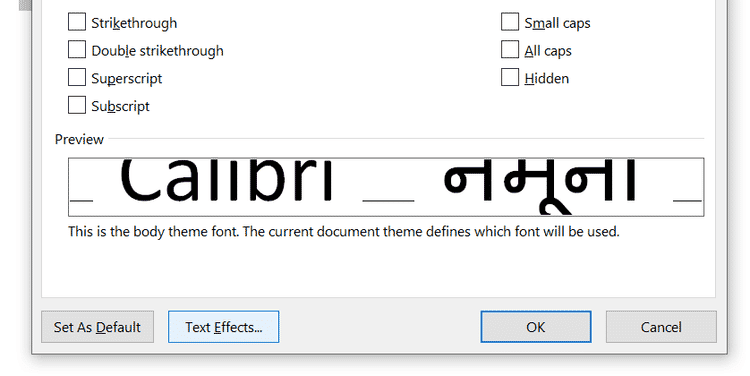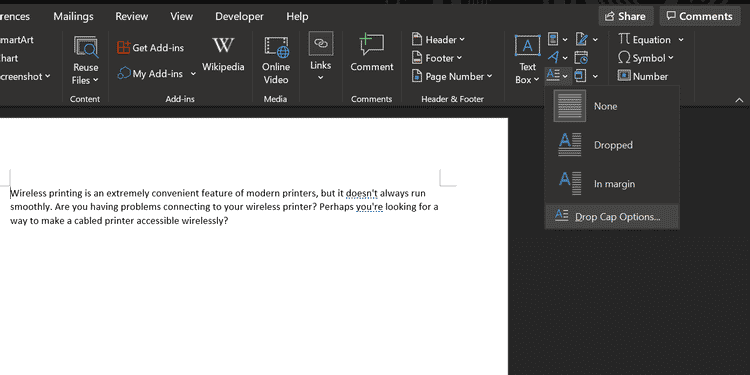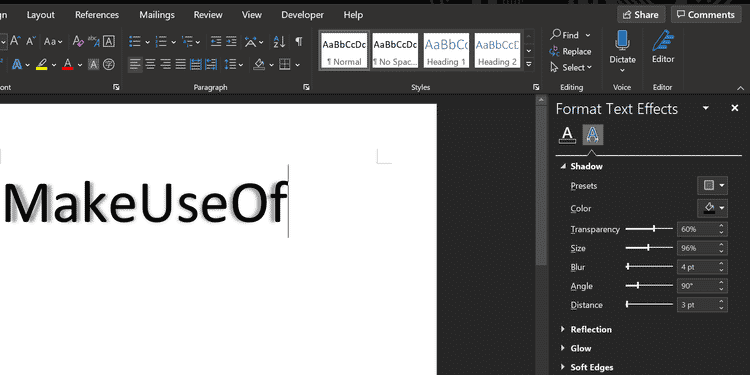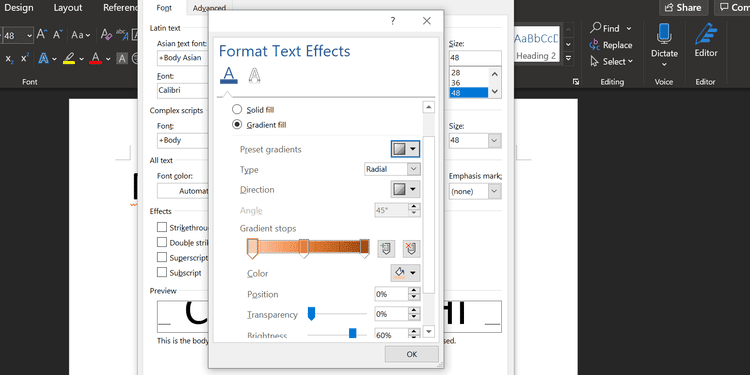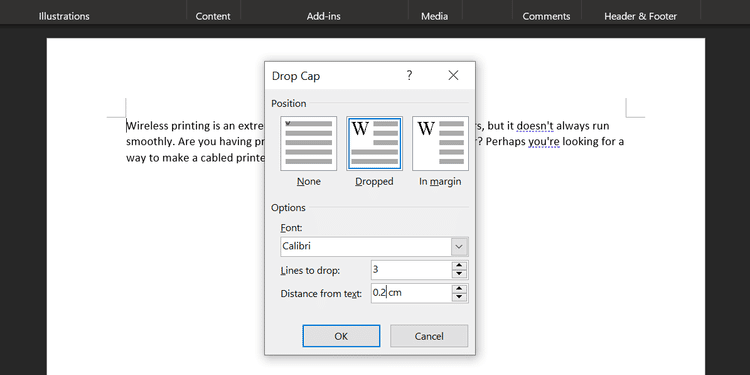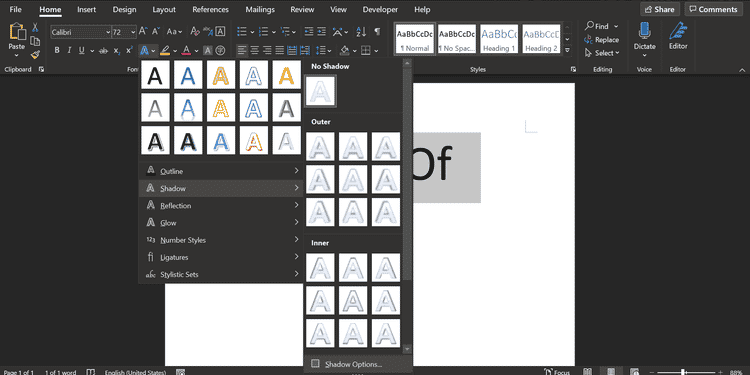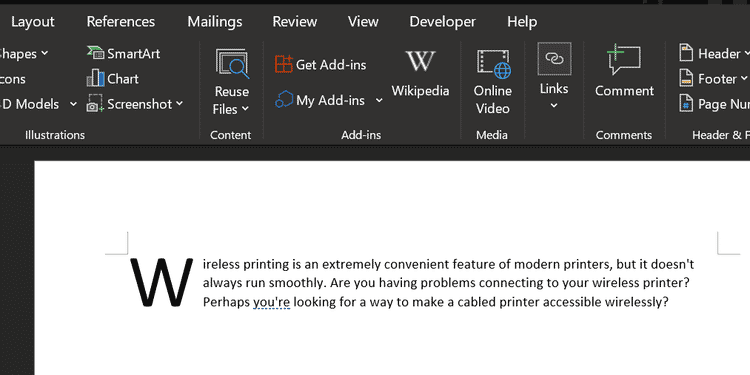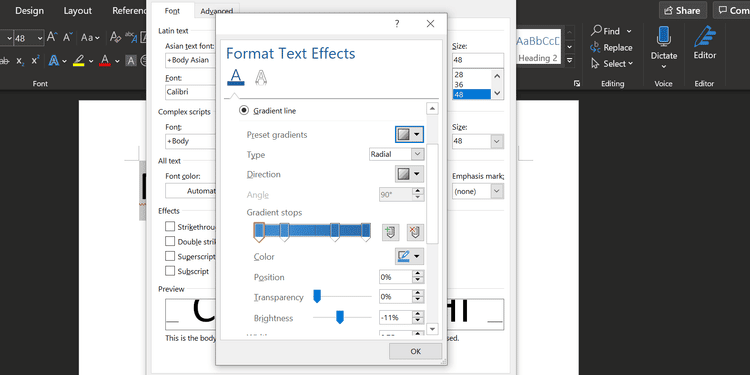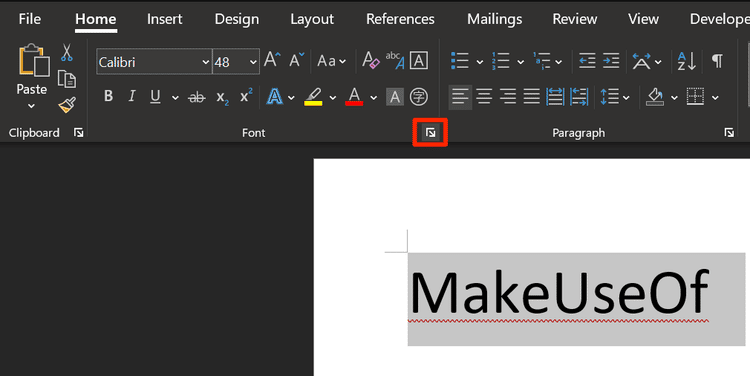
لمجرد رؤية صفحات من النص العادي يُمكن أن يجعل جفونك تبدأ في التدلي. تُشير مستندات Word غير المُنسقة إلى أن هذه القراءة ستكون مُحبطة ومُملة. لا أحد يُريد أن يتحمل هذا النوع من الملل.
يحتوي Microsoft Word على العديد من الأدوات التي يُمكن أن تجعل النص الخاص بك أكثر جمالا مع الخطوط الجمالية والتأثيرات الدقيقة. يُمكن للمبالغة في ذلك أن تملأ المستند بإلهاءات ، لكن الأسلوب المعقول في التصميم والديكور يُضيف اهتمامًا بصريًا مُهمًا للحفاظ على انتباه القارئ.
إليك بعض أنماط الخطوط وتأثيراتها لإبراز النص في Microsoft Word.
1. تثبيت الخطوط الجمالية لـ Microsoft Word
تتمثل إحدى أسهل الطرق لإضفاء الحيوية على النص في Word في إضافة بعض الخطوط الجديدة. يُمكنك العثور على الكثير من الخطوط المجانية عبر الإنترنت ، ولكن الأمر يستحق أخذ لحظة للنظر فيما إذا كنت تريد استخدام تنسيق OTF أو TTF قبل أن تبدأ البحث.
هذه إصدارات معدلة قليلاً من الخط بأبعاد معدلة — يمكن أن تكون مفيدة جدًا إذا كنت تبحث عن الكمال ، ولكن سيتم تقديم خدمة جيدة لمعظم المُستخدمين من خلال الإصدار العادي وحده.
ثم ببساطة حدد الخط الجمالي الجديد من خيارات التنسيق داخل Microsoft Word.
2. إضافة ظل بسيط
الظل المُسقط هو أسلوب تصميم رسومي كلاسيكي يُمكنك استخدامه لإبراز النص. يُقدم Word عدة طرق مختلفة لتحقيق ذلك ، ويُمكنك استخدام قائمة تأثيرات النص والكتابة للقيام بذلك.
أولاً ، اكتب النص الذي تُريده ونسق حجمه وخطه وفقًا للمُواصفات التي تُفضلها — ستحتاج إلى تحديد الشكل الذي تُريده أن يبدو عليه قبل إنشاء الظل الخاص بك. حدد النص الخاص بك باستخدام الماوس ، وانقر فوق أيقونة تأثيرات النص وصياغة الحروف (الزر A الأزرق) ، ثم حدد ظل متبوعًا بـ خيارات الظل.
سيتم فتح قائمة جديدة على اليمين تُتيح لك تخصيص الظل. إما أن تنقر فوق خيار الإعدادات المسبقة واختر أحد خيارات الظل العديدة أو اضبط الإعدادات المُختلفة بنفسك لإنشاء ظل مخصص.
سترى المعاينة المباشرة على يسار قائمة الظل.
استمر في تغيير الخيارات حتى يظهر الظل بالطريقة التي تُريدها. يُمكنك بعد ذلك النقر فوق الرمز X في الزاوية العلوية اليمنى من قائمة الظل لإغلاقها. يحفظ Word التغييرات التي تم إجراؤها على النص تلقائيًا.
3. إضافة حرف استهلالي مسقط
الحرف الاستهلالي المسقط هو الحرف الأول الكبير من الفقرة ، وغالبًا ما يوجد في الروايات القديمة. يُمكن لـ Microsoft Word تجهيز المستند الخاص بك بهذا العنصر الزخرفي الذي يجذب الانتباه في غضون ثوانٍ ، مما يمنحك وسائل إضافة الاهتمام إلى كتلة كبيرة من النص ، أو ببساطة استدعاء إلى الذهن حقبة كلاسيكية.
توجه إلى قسم النص في علامة التبويب إدراج وابحث عن القائمة المنسدلة إسقاط. ستتمكن من إنشاء حرف استهالي بسيط للغاية عن طريق تحديد إما تم إسقاطه أو في الهامش هنا ، ولكن للحصول على أفضل النتائج ، ستحتاج إلى النقر فوق خيارات اسقاط الأحرف الاستهلاكية ، بينما تم تحديد الحرف الأول من الفقرة.
حدد تم إسقاطه واضبط المسافة من النص إلى 0.2 سم (0.08 بوصة). قد تحتاج إلى تعديل المقدار ، اعتمادًا على الخط الذي تستخدمه والمقياس الذي تعمل به ، ولكن يُمكن أن يبدو الحرف الاستهلالي أحيانًا غير جيد مقارنةً بمسافة الأسطر القياسية عند تركه عند 0.
سيكون اختيارك للخط هو المفتاح للتأثير الكلي. يمكن أن يعمل sans font بشكل جيد إذا كان هدفك الأساسي هو مظهر لافت للنظر ، ولكن يمكن تحقيق غطاء مسقط تقليدي أكثر باستخدام خط serif الأكثر وضوحًا.
4. استخدام تأثيرات النص
إذا تم استخدامها بلا مبالاة ، يُمكن لتأثيرات النص المُتوفرة في Microsoft Word أن تُذكر بسهولة بأسوأ تجاوزات WordArt. ومع ذلك ، طالما أنك لا تفرط في استخدامها ، يمكن أن تمنح هذه التأثيرات المستند الخاص بك بعض التأثير البصري الحقيقي.
للوصول إلى قائمة تأثيرات النص ، توجه إلى علامة التبويب الصفحة الرئيسية وانقر فوق الزر المنبثق في قسم الخطوط.
ثم انقر فوق الزر تأثيرات النص في النافذة التي تفتح.
تعبئة النص
يEعد خيار تعبئة النص طريقة رائعة لإضافة بعض الألوان إلى جزء من النص. ستطبق التعبئة الخالصة لون واحد فقط على اختيارك ، والذي يُمكن القيام به بضجة أقل ، لكن خيار التعبئة المتدرجة يوفر الكثير من الفروق الدقيقة لأي مصمم جرافيك ناشئ.
بالإضافة إلى العديد من الإعدادات المسبقة ، يمكن استخدام قائمة التدرج اللوني للتركيز على مزيج لوني معين لملء النص به. يُمكنك إضافة وإزالة نقاط توقف التدرج باستخدام الزرين إلى أقصى نهاية خط اللون ، ثم ضبط الألوان الفردية من خلال النقر على نقطة التوقف المقابلة والتلاعب بقائمة الألوان المنسدلة الموجودة أدناه مباشرة.
يمكنك الحصول على بعض التأثيرات الرائعة باستخدام التعبئة المتدرجة ، ولكن من المهم أن تختار ألوانك بعناية للتأكد من أنها تعمل بشكل جيد معًا. تذكر أن تختار الألوان ومجموعات الألوان بناءً على جمهورك المستهدف.
تأثير النص التفصيلي
يمكنك أيضًا استخدام تأثيرات النص لإضافة مخطط تفصيلي إلى النص الخاص بك ، والذي يمكن أن يساعد حقًا في إبراز الكلمات على الخلفية. للبدء ، توجه إلى قائمة تتأثيرات النص مرة أخرى ، ولكن هذه المرة انقر على القائمة المنسدلة تأثير النص التفصيلي.
سترى خيارات الخط الثابت وخط التدرج ، تمامًا كما فعلت في قسم التعبئة من القائمة سابقًا.
يعمل إعداد التدرج اللوني تمامًا كما هو مذكور أعلاه ، على الرغم من أنه من الواضح أن النتائج ستكون أكثر دقة قليلاً لأن المخطط التفصيلي فقط هو الذي سيتأثر ، بدلاً من النص نفسه. استخدم حقل العرض لضبط مدى ثخانة المخطط التفصيلي حتى تصبح راضيًا عن النتائج.
5. ضبط تباعد الأحرف
قد يبدو ضبط المسافة بين الأحرف الفردية للنص بمثابة تعديل بسيط ، ولكن يمكن أن يكون له تأثير قوي على مظهر النص العام وحتى قابلية قراءته.
أهم شيء يجب تذكره عند ضبط تباعد الأحرف هو أنَّ الأقل هو الأكثر. يتم توجيه الكثير من العناية والاهتمام إلى تصميم الخط ، لذلك ليس من الحكمة دائمًا إجراء تعديلاتك الخاصة. ومع ذلك ، في بعض الأحيان ، يحتاج جزء صغير من النص البارز مثل العنوان إلى بعض التعديلات قبل أن يبدو صحيحًا.
للبدء ، تأكد من إعداد النص وفقًا لمواصفاتك من حيث الحجم والخط — يجب أن تكون التعديلات على تباعد الأحرف هي الخطوة الأخيرة نحو تحسين النص. بمجرد أن تصبح جاهزًا ، قم بتحديد المنطقة التي تُريد تعديلها وانقر فوق الزر المنبثق في قسم الخط في علامة التبويب الصفحة الرئيسية.
توجه إلى علامة التبويب خيارات متقدمة في النافذة التي تفتح وابحث عن قسم تباعد الأحرف. هنا ، يُمكنك استخدام القائمة المنسدلة التباعد للتبديل بين موسع و مُكثف لنقل الأحرف بعيدًا أو بالقرب من بعضها. استخدم حقل الإدخال على اليمين لتحديد مدى رغبتك في تغيير التباعد.
بمجرد تجربة عناصر التحكم هذه قليلاً ، يجب أن تكون قادرًا على استخدام هذه الخيارات لضبط النص الخاص بك. على سبيل المثال ، قد تعمل بعض الخطوط بشكل أفضل إذا تم تجميع الأحرف بالقرب من بعضها البعض ، خاصةً إذا كان الخط الطباعي يعتمد على الكتابة اليدوية أو فن الخط.
بدلاً من ذلك ، يمكنك توسيع تباعد الأحرف لبعض النصوص لجعله عريضًا بدرجة كافية لملء فراغ دون زيادة ارتفاعه. هذه التقنية فعالة بشكل خاص عند دمجها مع خطوط أكثر بساطة.
اجعل النص يتدفق في Word
مع التنسيق الجيد ، لا يبدو النص الخاص بك أكثر إرضاءً فحسب ، ولكنه يُوفر أيضًا نقاط ارتساء للعيون ويساعد القارئ على التدفق خلال المستند.
هناك الكثير من قواعد التصميم لـ Microsoft Word التي يُمكنك اتباعها لمنح مستنداتك لمسة احترافية. هذه القواعد تستحق التعلم إذا كنت تقضي وقتًا طويلاً مع Word.